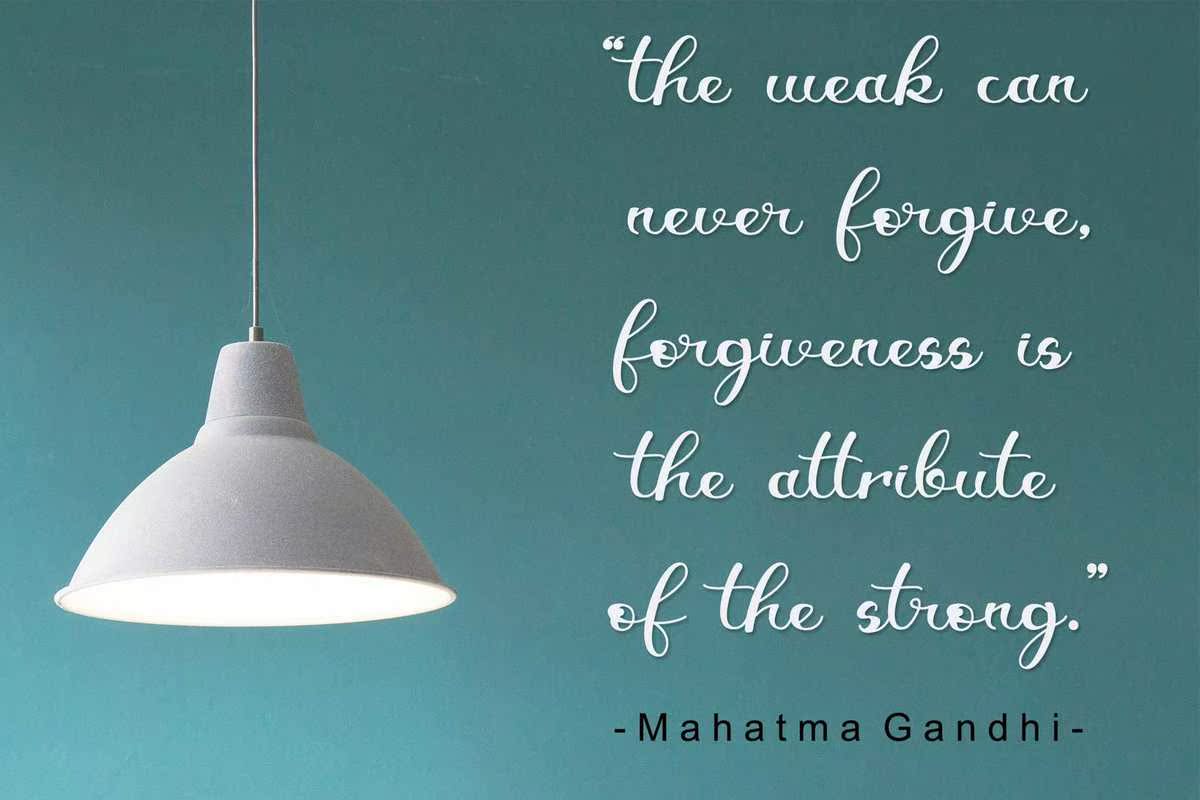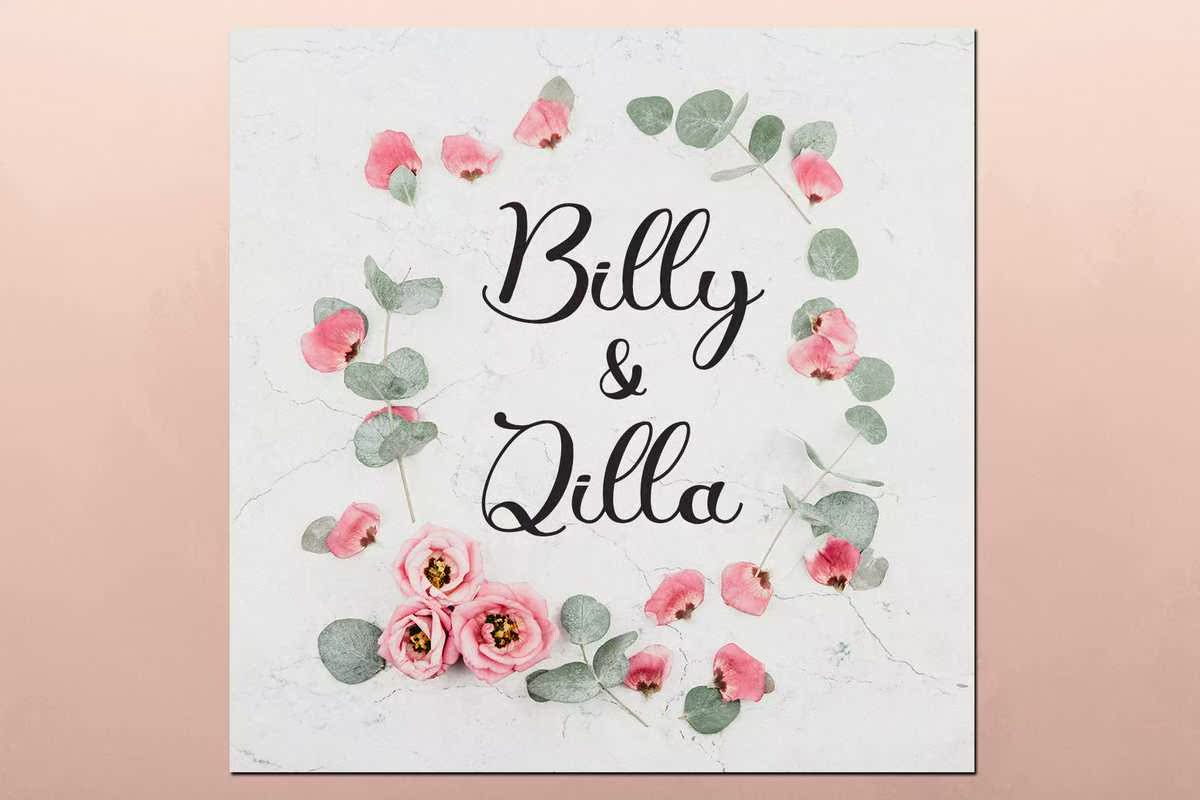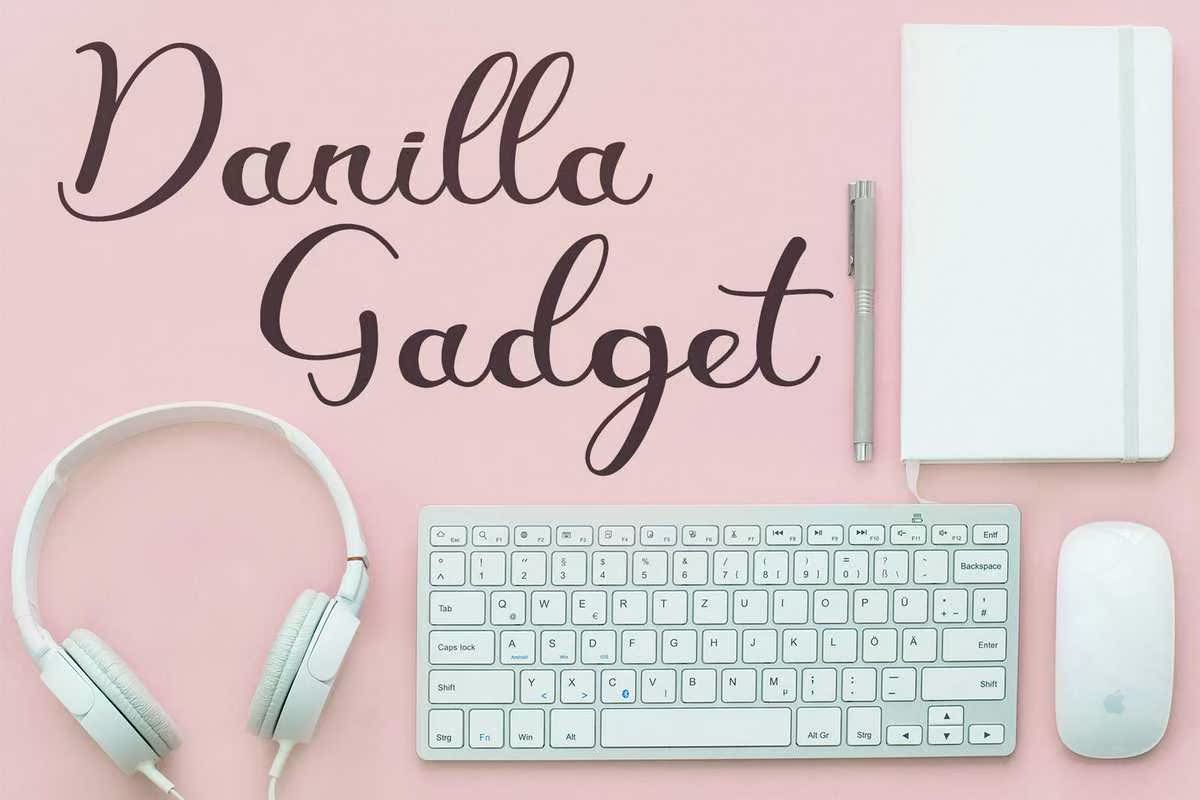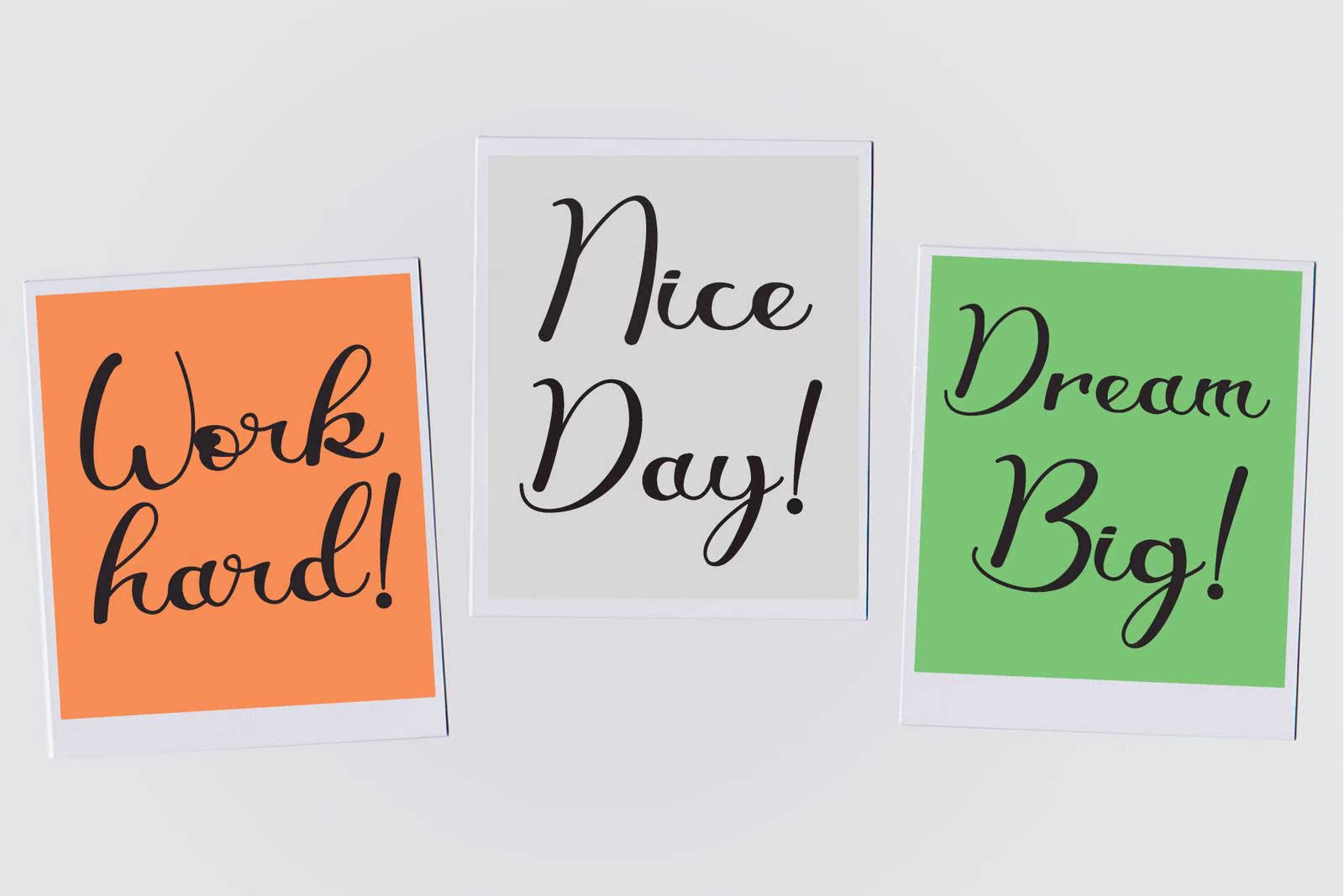
LovebirdFontByletterRafaStudio新推出的LovebirdFontFontByletterRafaStudio。它具有流动的字母,可以让您的设计在一周内清晰可见,并配有可爱的标题。Lovebirdfontisperfect;欢迎卡、包装设计、耐磨性、工艺设计、任何DIY项目、书名、婚礼宣传、包装等。LoveBirdFontByletteRafaStudio提供的LovebirdFontisoneofmanyfontbyLetterafaStudio。其流动字母将使您的设计更具吸引力,并在周内配备Lovebirdfontisperfect;贺卡、包装设计、耐磨性、工艺设计、任何项目、书名、婚礼宣传、包装等等。